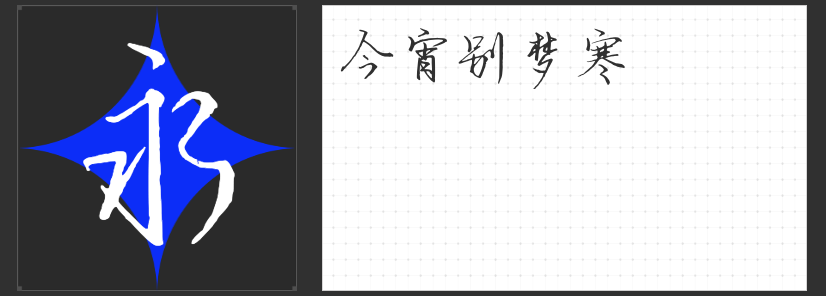
四款设计感手写字体推荐:让创意笔触唤醒视觉生命力
在商业设计与创意表达中,手写字体的独特温度与艺术张力,能为作品注入鲜活的个性。以下四款非免费手写字体,以各自鲜明的风格与强大的适配性,成为设计师笔下的“点睛之笔”。
一、励字造仲夏简 常规
这款字体以“清新文艺”为底色,将传统书法的骨力与现代设计的简洁融为一体。笔画坚挺爽利,边缘斑驳的细节赋予其手作质感,而钩笔的洒脱处理则暗藏力量感。字形端正不失灵动,无论是商业海报的视觉冲击,还是包装设计的精致感,亦或是短视频标题的动态呈现,都能以恰到好处的分寸感平衡艺术性与实用性。
二、字青春悸动简 常规
以“端正”为骨架,以“清秀”为血肉,这款字体通过细腻的笔画处理传递出青春的悸动感。字形结构清晰,既保留手写的自然韵律,又具备印刷体的规范感,适用于短视频字幕的轻快节奏,也能为海报标题增添一抹清新气质,是年轻化品牌视觉的优选。
三、云书法玉兰行楷体
作为一款气韵生动的毛笔字体,它以刚柔并济的笔触重构传统行楷的魅力。主笔画块面感强烈,层次分明;牵丝连带的设计让文字如流水般连贯,运笔的节奏感跃然纸上。从文创产品的文化底蕴,到影视海报的视觉张力,再到书籍封面的意境营造,这款字体总能以书法的流动性赋予设计灵魂。
四、MyFont骊歌钢笔简繁 细体
以“多变”与“飘逸”为核心,这款字体通过自由开合的结体与灵动的牵丝设计,模拟出钢笔书写的自然轨迹。细体线条轻盈却不失力量,排版后如乐章般富有韵律感,尤其适合需要传递情感与故事性的场景——无论是广告设计中的品牌叙事,还是包装设计中的细节点缀,都能以独特的“旋律感”引发观者共鸣。
这四款字体,或刚劲或柔美,或传统或现代,以手写的温度为设计注入不可复制的灵魂。选择它们,便是为创意选择了一种更富生命力的表达方式。